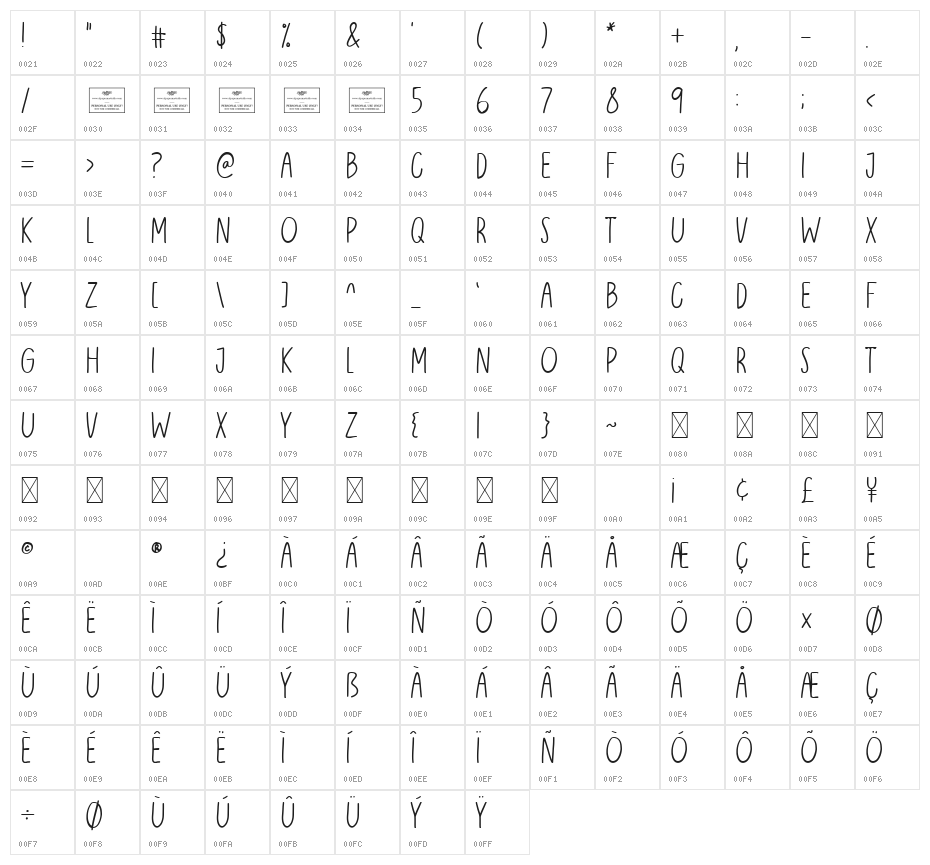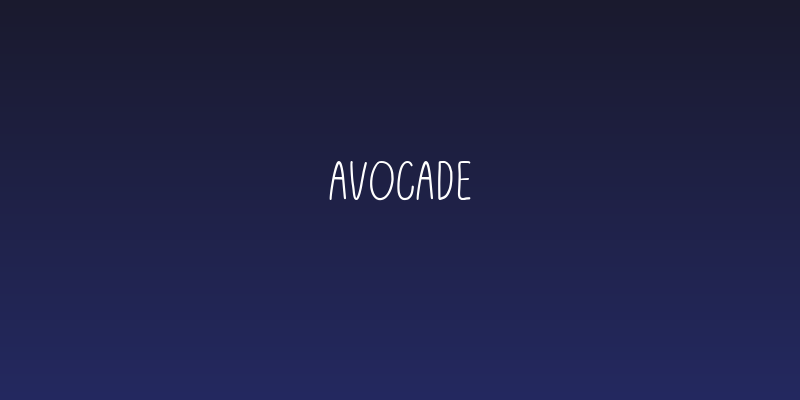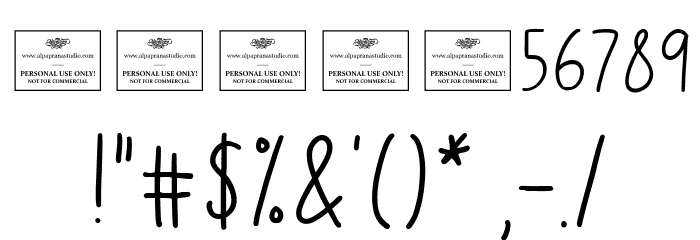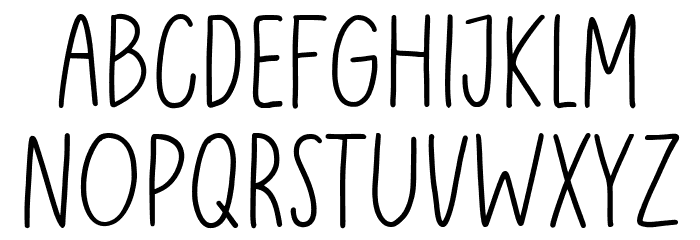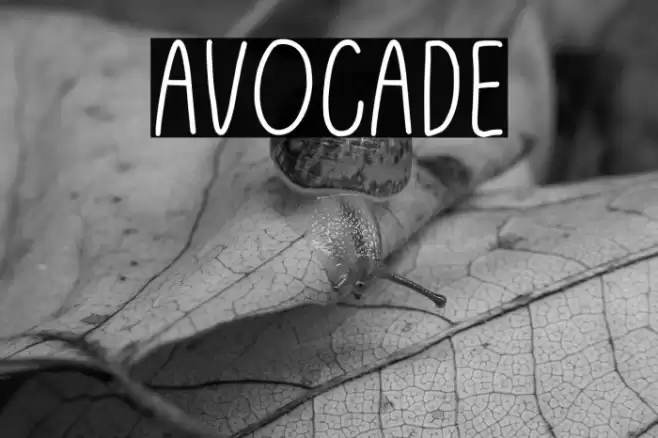
Avocade Font
| Gesamtstil | Casual, Playful |
| Anwendungsfall | Headlines, Informal text, Creative projects |
| Vorgeschlagene Projekte | Ideal for greeting cards, children's books, playful branding, and social media graphics. |